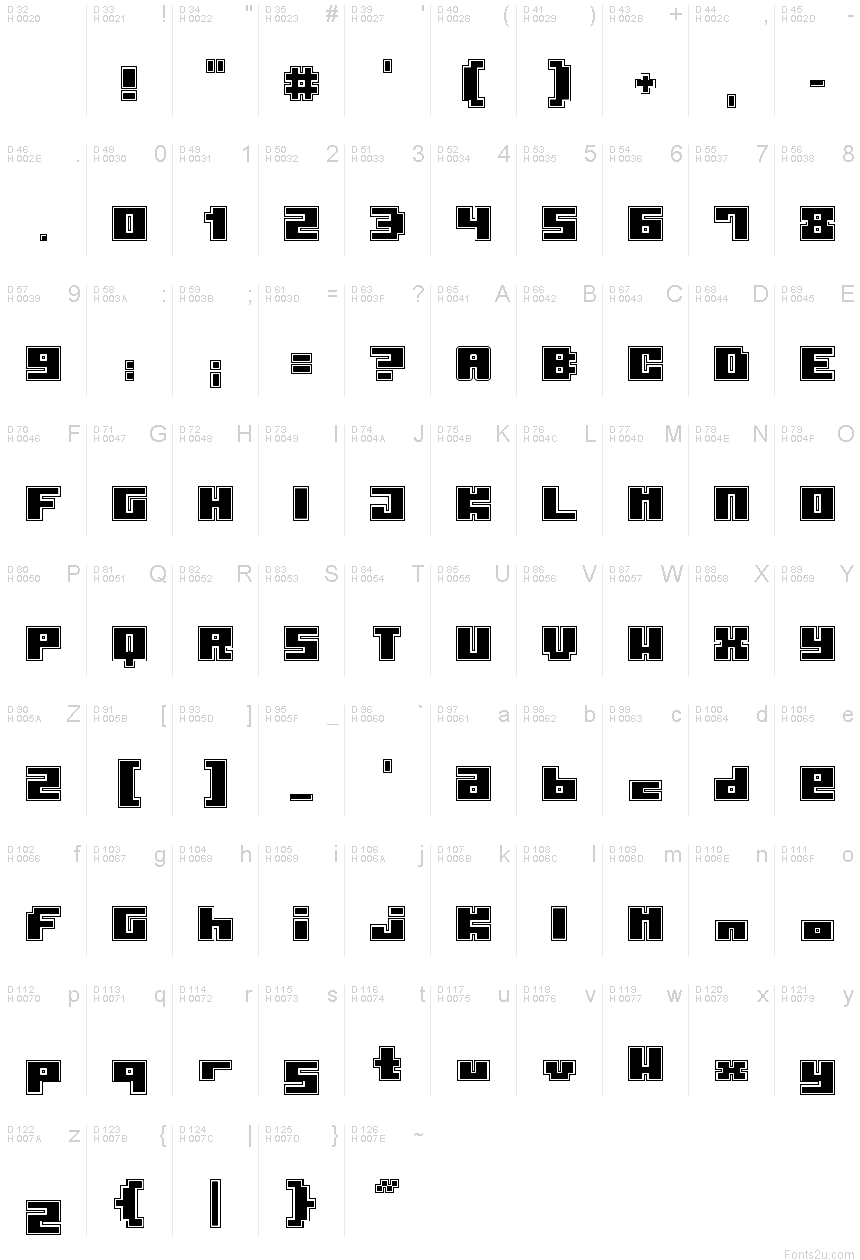
Pormask Innebrannare od TarmSaft Font Factory to darmowy, techniczny krój pisma typu display, inspirowany estetyką płytek drukowanych. Litery wyglądają, jakby zostały wycięte z grubych, prostokątnych bloków, wydrążone kwadratowymi kanałami i drobnymi otworami, co nadaje całemu alfabetowi modularny, futurystyczny charakter w klimacie retro-gier.
Świetnie sprawdzi się w nagłówkach plakatów, wizerunkach marek inspirowanych grami arcade, okładkach science-fiction czy kompaktowych logotypach, gdzie te labiryntowe wycięcia grają główną rolę. Jako darmowy font, nadaje się również do opraw albumów i krótkich napisów w interfejsach, zwłaszcza gdy chcesz, aby wielkie litery czytały się jak graficzny system, a nie zwykły tekst.